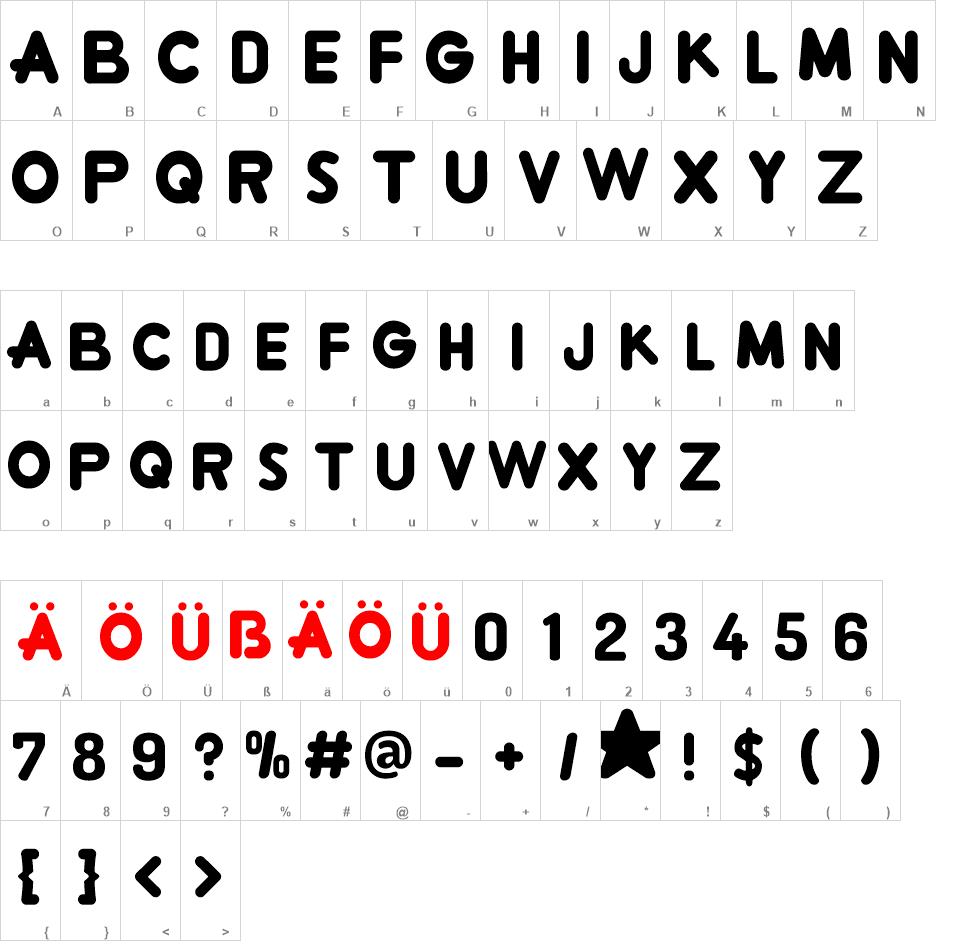
Crewniverse
Crewniverse ist eine Schrift, die die für die Titelkarten der TV-Serie Steven Universe ™ verwendete Schriftart sowie das Logo des Steven Crewniverse Tumblr nachbildet.